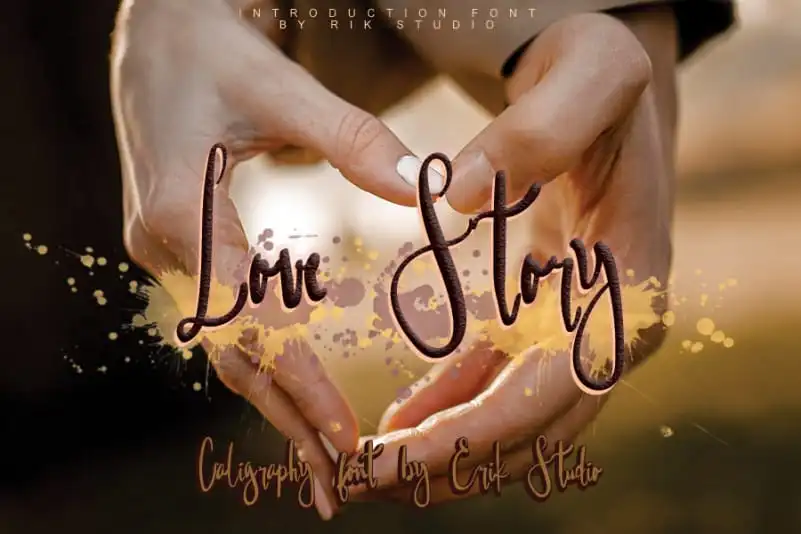
Love Story Font – Fonte Grátis
Love Story Font
Agora é a hora de enfeitar seus projetos design com um toque romântico e autêntico. Introduzimos Love Story Script Font, uma elegante mistura de letra manuscrita casual e fluida. Perfeito para qualquer projeto gráfico que busque uma aparência encantadora e acolhedora. Convidamos você a experimentar o charme natural dessa fonte, ideal para capas de livros, cartões de aniversário, letras do seu blog ou até mesmo como título em sua página de redes sociais. Love Story Script é a escolha perfeita para aqueles que valorizam um toque pessoal e inconfundível em seus trabalhos. Escolha Love Story Font e faça de cada projeto uma história. Esse script manuscrito é especialmente criado pelo talentoso designer Erik Studio, conhecido por produzir fontes com características únicas e encantadoras. Através dele, você pode adicionar um toque autêntico a qualquer design que desejar. Não importa se está trabalhando em uma apresentação de PowerPoint ou criando material para seu site web, Love Story Script é o ideal para aqueles que valorizam textos com um ar romântico e personalizado. Experimente agora e inspire-se com essa fonte única, perfeita para destacar sua elegância no design gráfico.